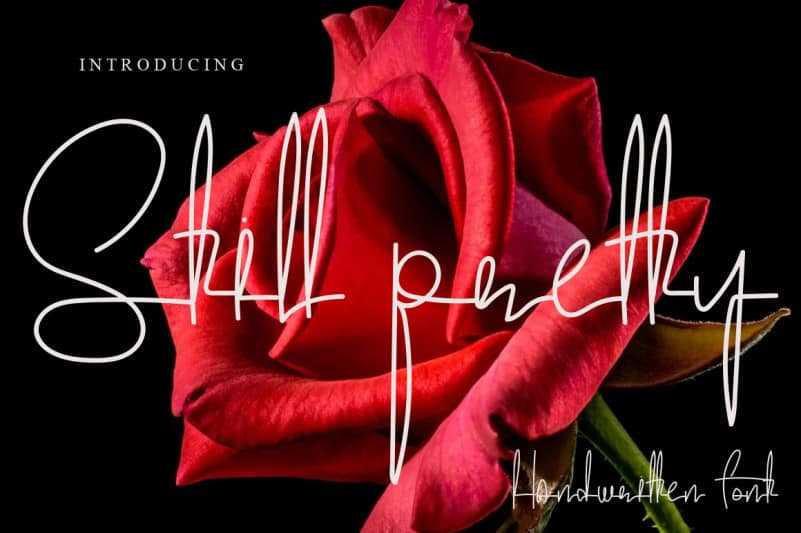
Still Pretty Font – Download Grátis
Ainda Pretty Font é uma fonte elegante criada à mão que se destaca por sua simplicidade e finura. Seja para títulos ou textos mais sutis, ela se adapta perfeitamente sem comprometer a beleza ou o estilo original. Este handwritten font possui um potencial incrível de transformar qualquer projeto em algo extraordinário. Com ainda Pretty Font no seu arsenal de fontes, você ganha uma opção versátil que pode ser aplicada em diversos ambientes e temáticas. Seja para criar anúncios impactantes ou artigos de moda, o resultado será um design atraente e sofisticado. Essa elegante fonte criada à mão é perfeita para quem valoriza tanto a simplicidade quanto a personalização única em seus trabalhos.